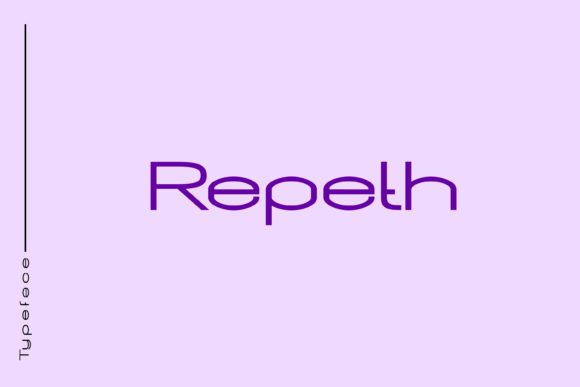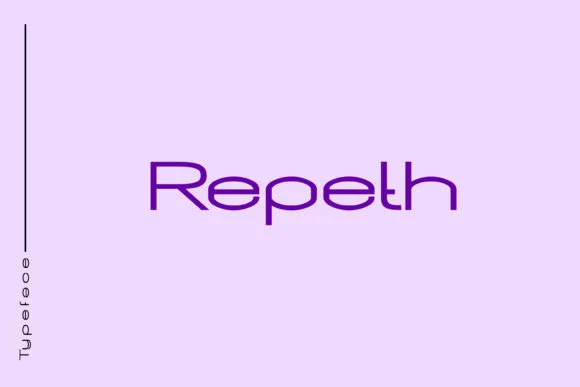
Название: Repeth Font (2021)
Repeth - это чистый и современный шрифт.
Добавьте этот минималистский шрифт в стиле техно в свой веб-дизайн, логотипы или почти все, что требует умного и холодного штриха.